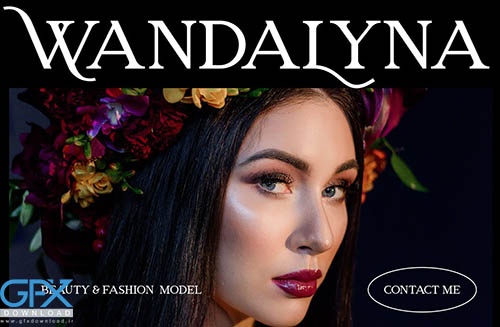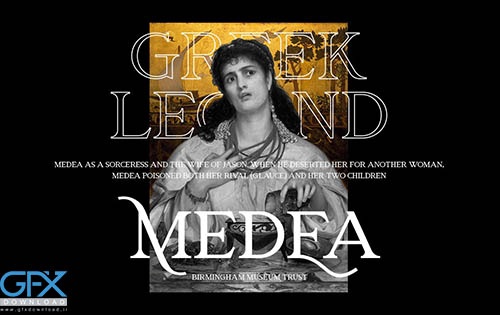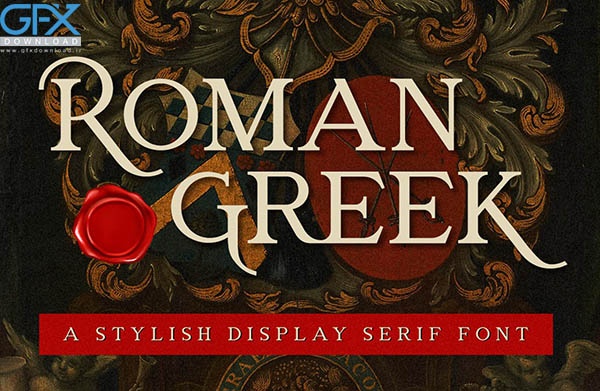
فونت رایگان یونانی رومی Roman Greek
یونانی رومی یک فونت Serif ظریف و متمایز است. این فونت که به دلیل سبک شیک و ساده‌ای که دارد، برای طرح‌های مختلف مناسب است، فونت رایگان یونانی رومی Roman Greek بدون توجه به موقعیت، این قابلیت را دارد که به فونت مورد علاقه شما تبدیل شود!